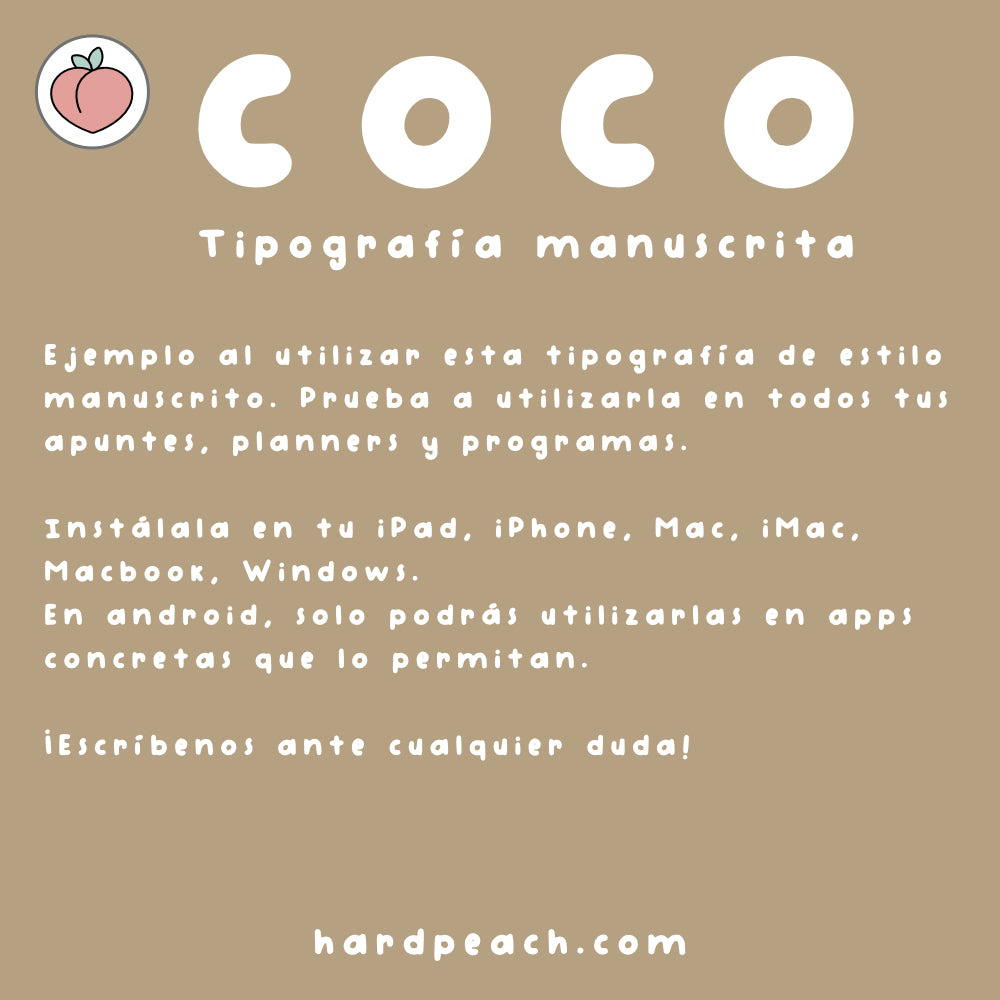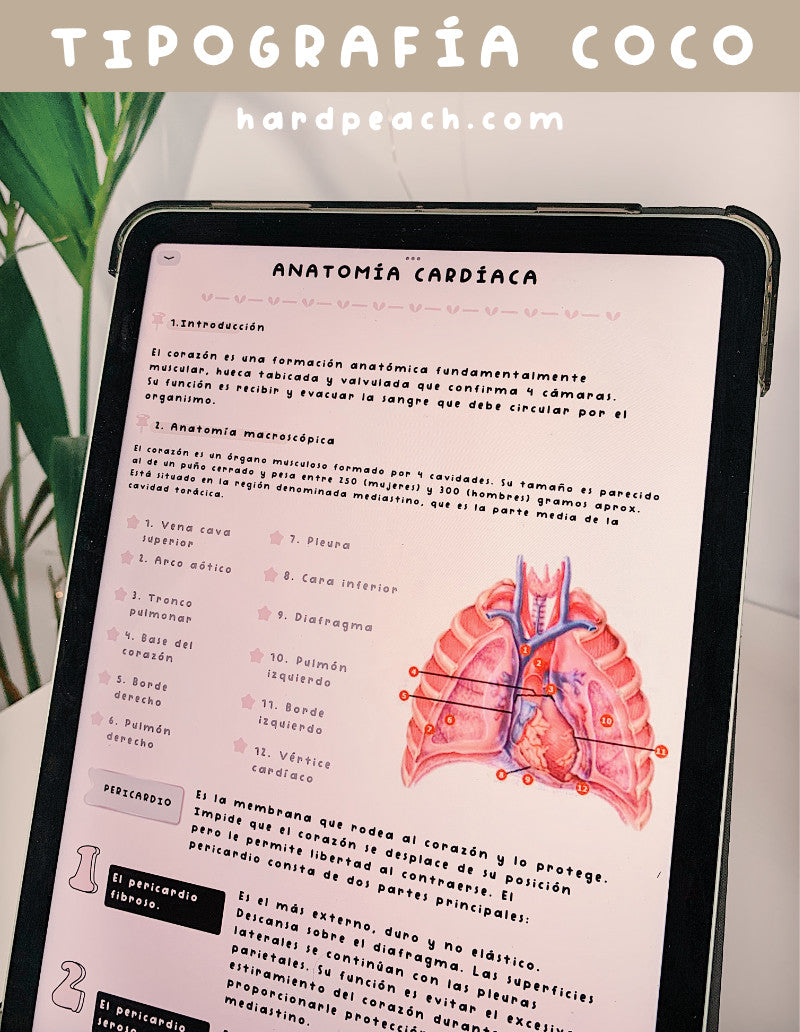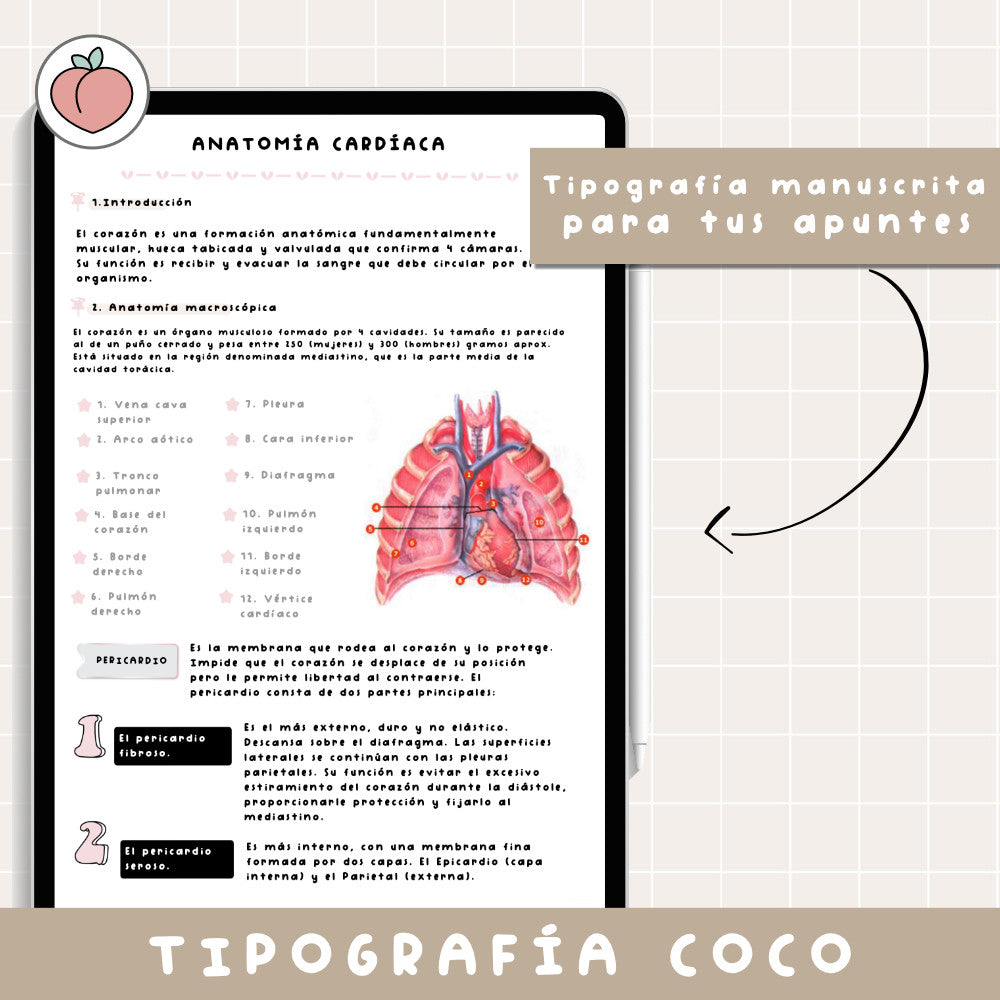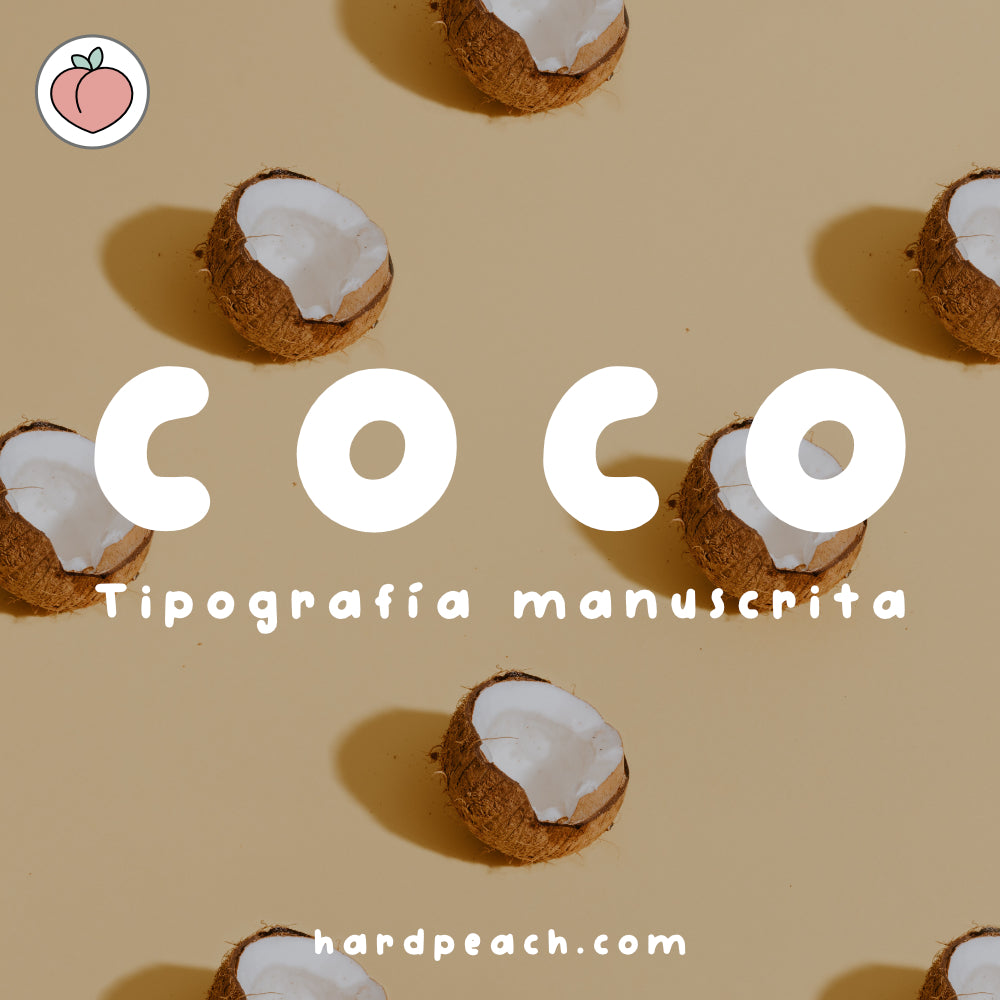
TIPOGRAFÍA MANUSCRITA COCO | FUENTE ESCRITA A MANO
Descubre nuestra tipografía manuscrita coco, diseñada para que puedas darle un estilo personal y profesional a todos tus apuntes digitales, anotaciones, resúmenes, títulos, esquemas, bullet journals y proyectos creativos. Con esta tipografía, tus textos digitales tendrán un toque único y elegante, perfecto para estudiantes, profesionales y cualquier persona que quiera destacar en sus documentos y diseños.
Ideas de uso:
- Apuntes digitales y para imprimir📝
- Anotaciones rápidas y esquemas organizativos 📚
- Títulos elegantes para documentos y presentaciones ✨
- Bullet journals, agendas y diarios creativos 🎨
- Proyectos de ilustración, diseño gráfico y lettering digital 🖌️
- Esquemas, diagramas y organización de ideas 📝
Convierte tus apuntes digitales, notas y proyectos creativos en algo especial con esta tipografía manuscrita, fácil de usar y compatible con tus dispositivos favoritos. Dale un toque de estilo y personalidad a todos tus textos, títulos y diseños con un trazo delicado y natural, pensado para facilitar tu trabajo y potenciar tu creatividad.
Esta tipografía incluye todos los caracteres principales, mayúsculas, minúsculas, números, vocales con tildes (español), y acentuaciones abiertas (à) y signos. Además, incluye la acentuaciones y las letras ñ y ç.